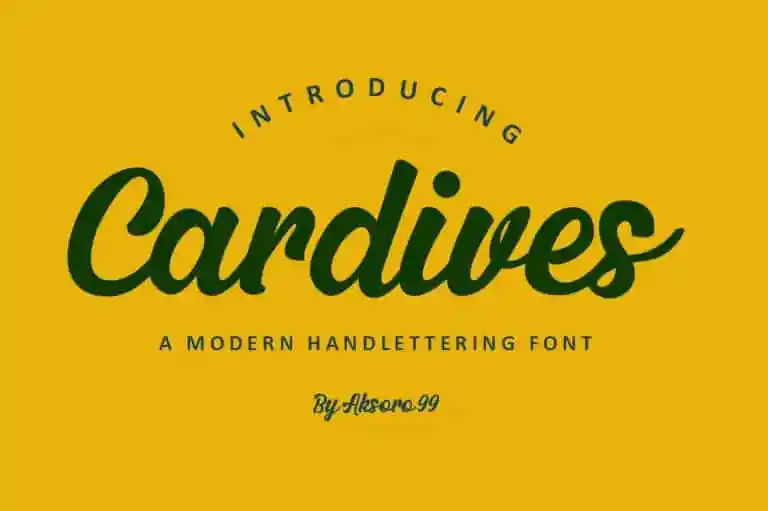
Cardives Script Font – Download Grátis
Cardives Script é uma fonte de tipo escrita inspirada no estilo tipográfico retro dos anos 60 e 70. Seu design naturalmente vem de palavras escritas a mão, mantendo tudo com sua essência artesanal. Esta elegante fonte é perfeita para qualquer projeto que você esteja desenvolvendo – desde logomarcas até banners e identidades visuais. Ela é uma adição incrível aos seus designs, tornando-os mais encantadores e poderosos. Ideal para quem quer dar um toque especial a suas criações digitais ou impressas, Cardives Script é uma excelente escolha para designers em todas as fases do processo criativo. Seja você alguém que busca inspiração no passado ou aquele que deseja inovar com estilo retro e versátil, este fonte é um ótimo complemento ao seu arsenal de recursos gráficos.